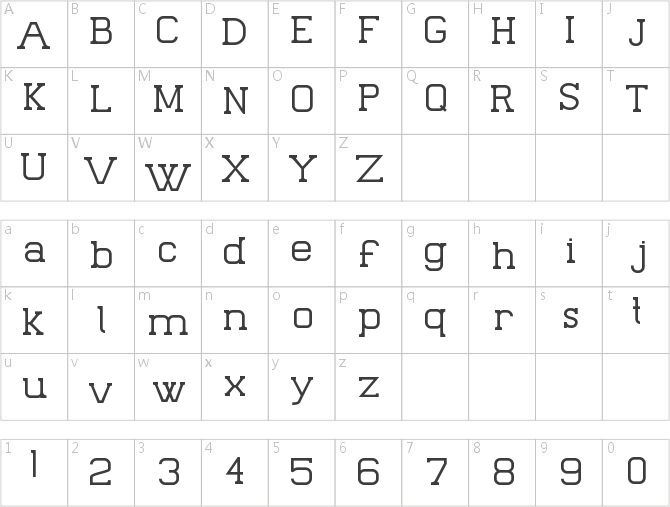
Palacio 詳情頁
字體名稱: Palacio
Palacio
Palacio字體字庫是一款讓人賞心悅目、百看不厭的英文字體,適合各類廣告和產(chǎn)品包裝設(shè)計(jì)應(yīng)用,字體大小0.03MB,格式為ttf字體,上傳用戶是眾聯(lián)齊成,作者/版權(quán)方為未知